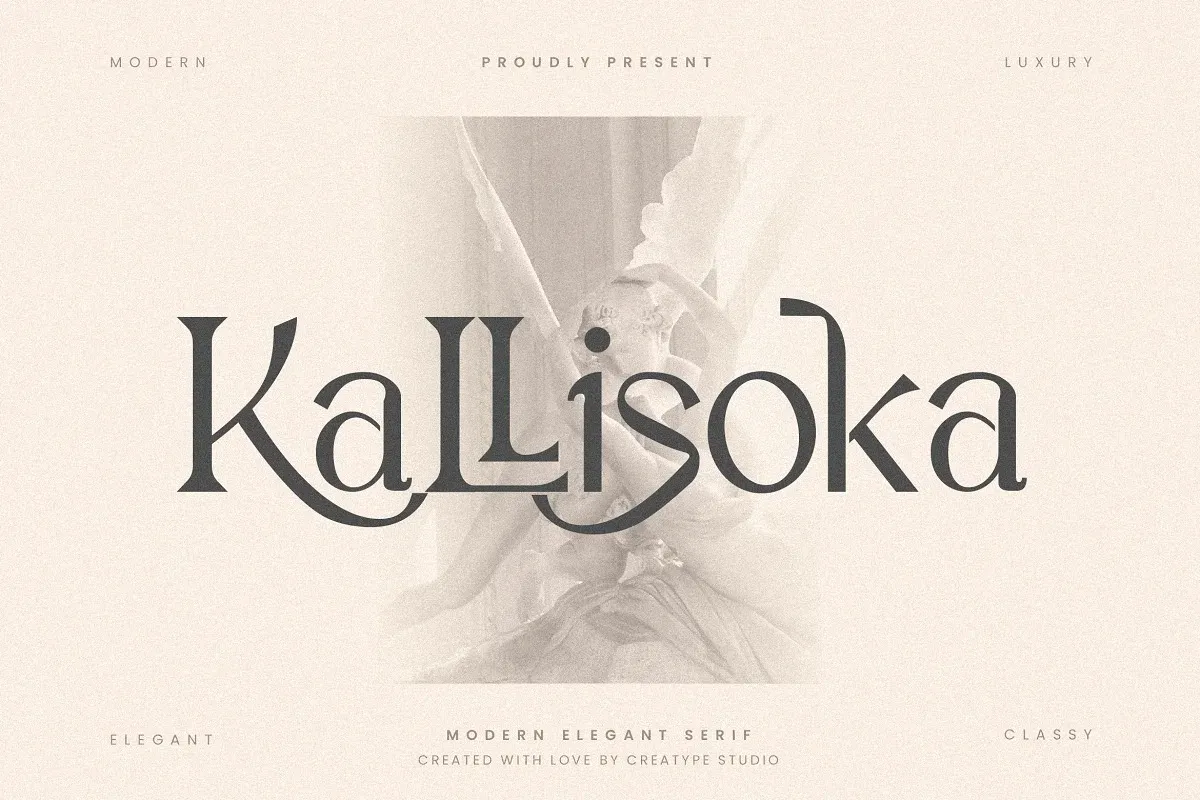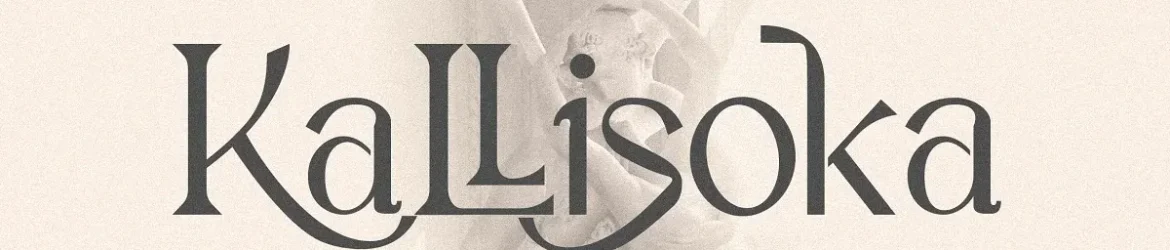
A Kallisoka Font é uma elegante tipografia serifada que combina refinamento com modernidade. Com ligaturas sofisticadas e alternativas pensadas para textos escritos a mão, ela foi cuidadosamente projetada para oferecer um fluxo fluido na hora de escrever. Criado pela Creatype Studio, este font é perfeito para adicionar uma pitada elegante aos seus trabalhos gráficos digitais. Com 18 ligaturas e 25 alternativas disponíveis, Kallisoka é a escolha ideal para quem busca uma mistura arredondada de estilo clássico e atualidade na sua fonte. Ideal tanto para nomes profissionais quanto para textos descritivos, esta font se destaca por oferecer um toque sofisticado que enriquece qualquer projeto gráfico.